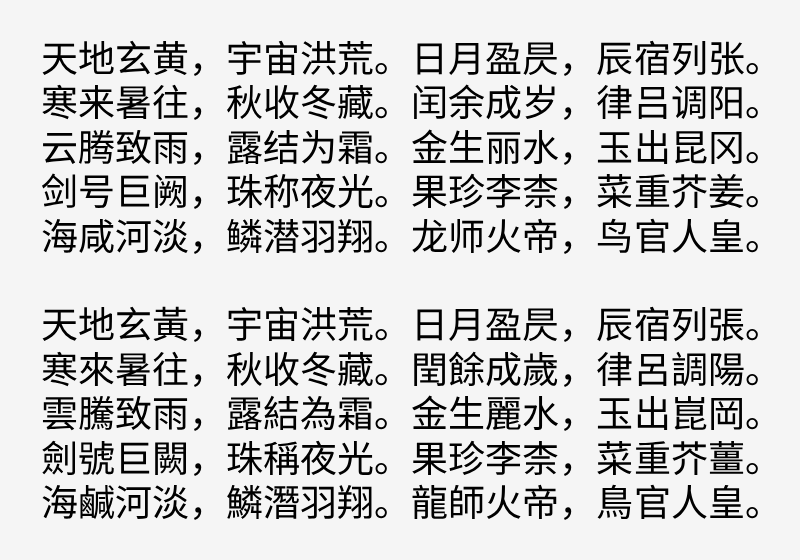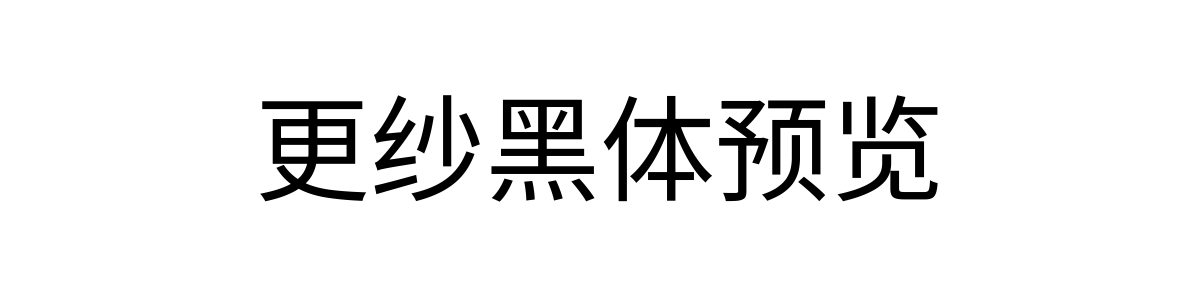
更纱黑体
更纱黑体(Sarasa Gothic)是一款面向中日韩与英文混排场景深度优化的开源免费字体,以 100% 缩放下极佳的屏幕显示效果和可读性为亮点。它由西文优质字体 Inter、编程等宽字体 Iosevka ,搭配思源黑体的 CJK 部分整合而成。
相比原版思源黑体,它的英文部分更现代、更具设计感,同时自带完整正体与斜体,屏幕显示效果也优于微软雅黑等系统默认字体。
字体风格
更纱黑体以屏幕实用为第一原则,将 Inter 的现代比例、Iosevka 的清晰结构与思源黑体的稳定字形融合在一起,让中英文在同一版面里灰度均匀、视觉协调。